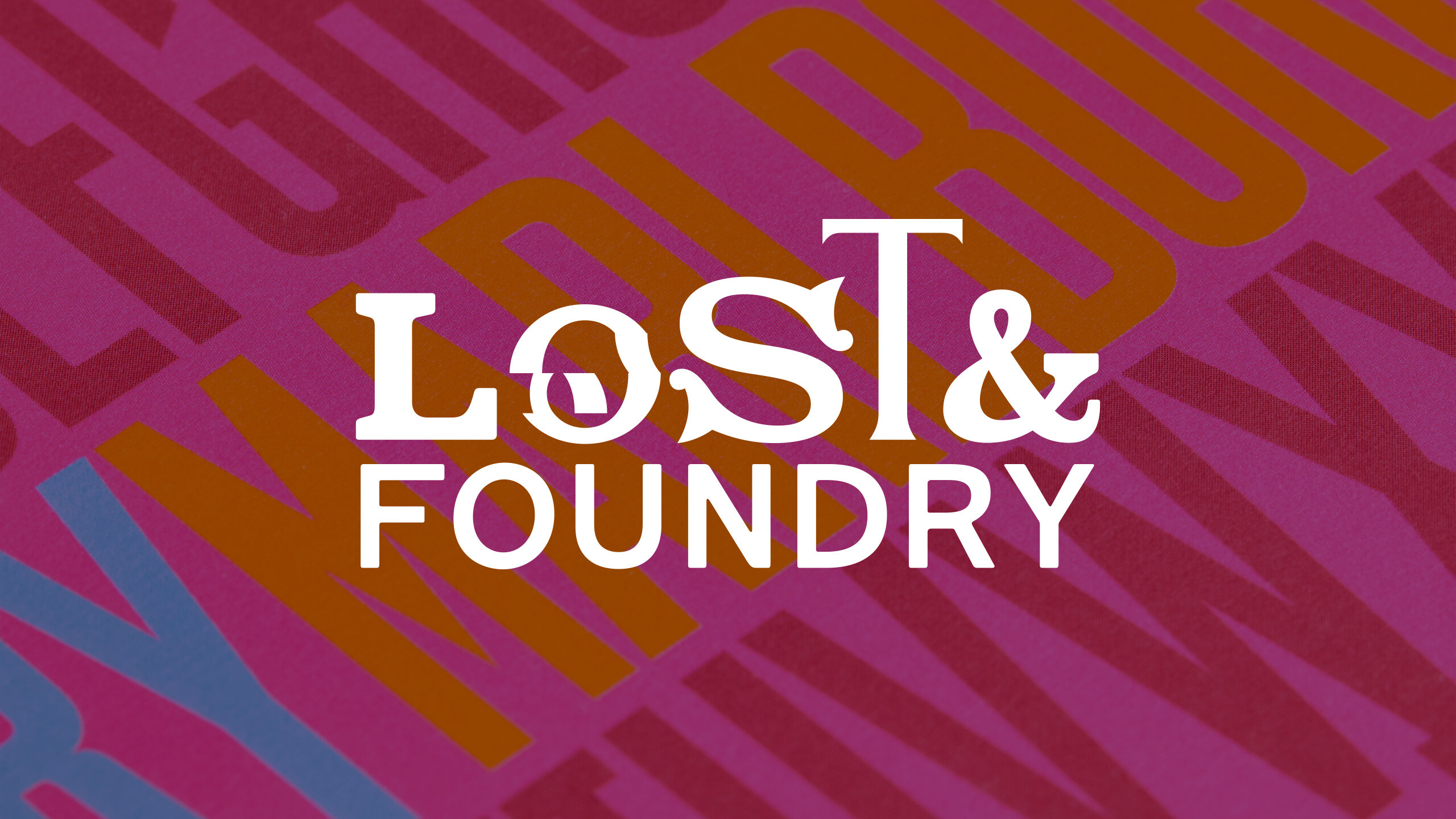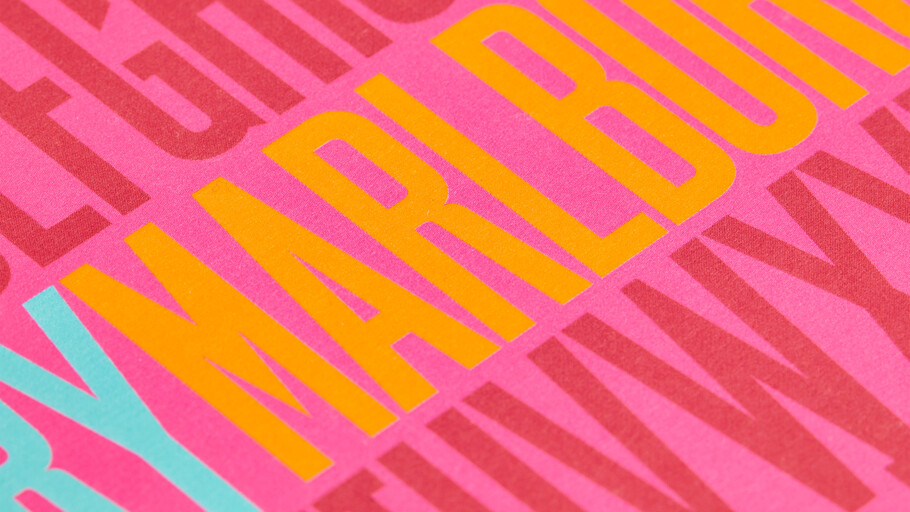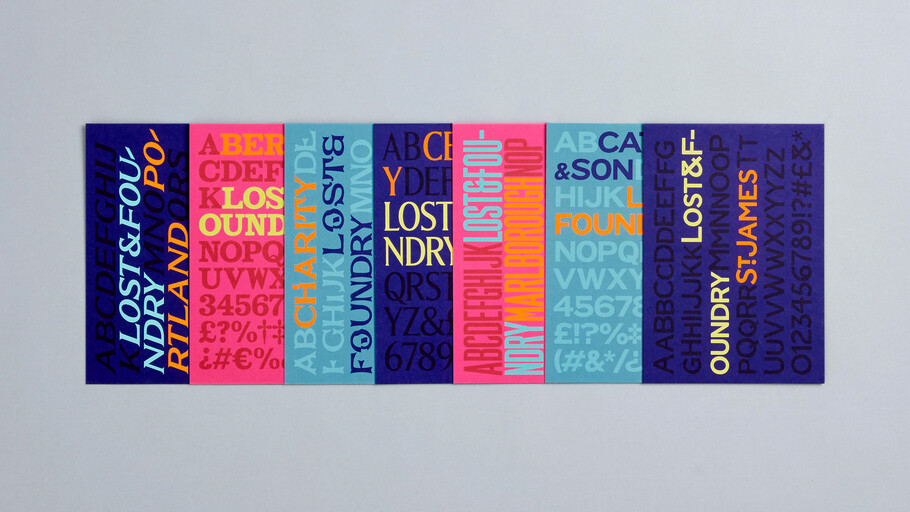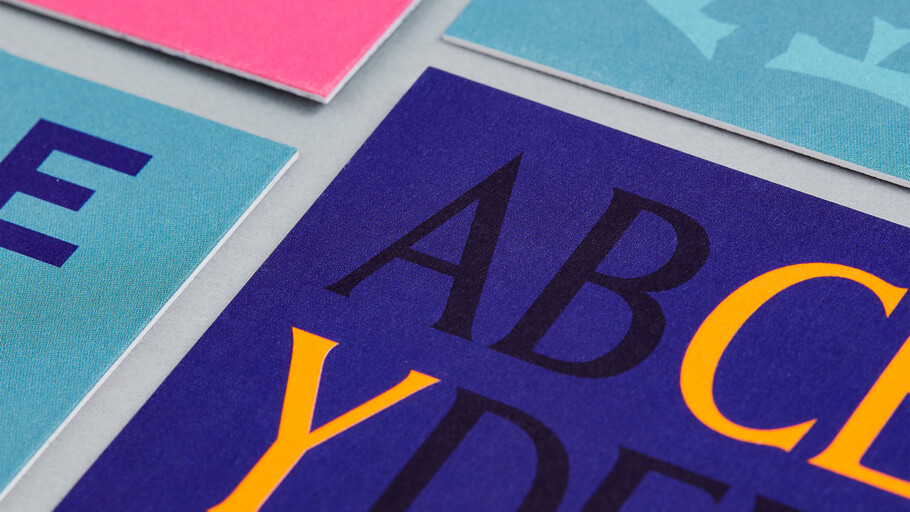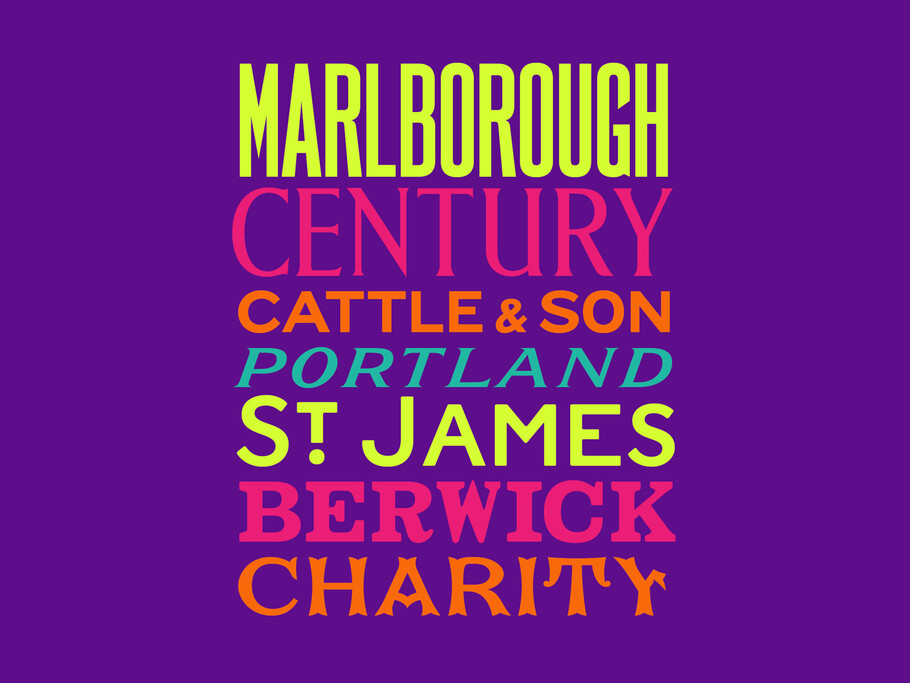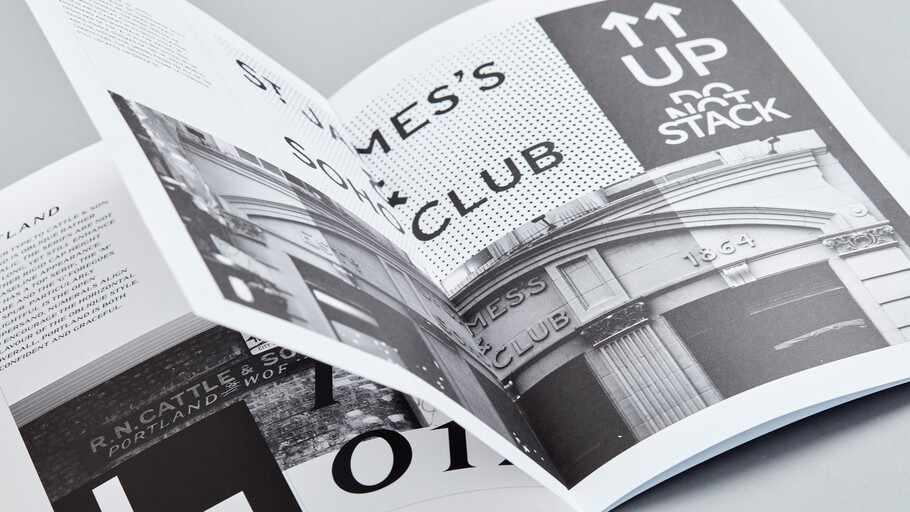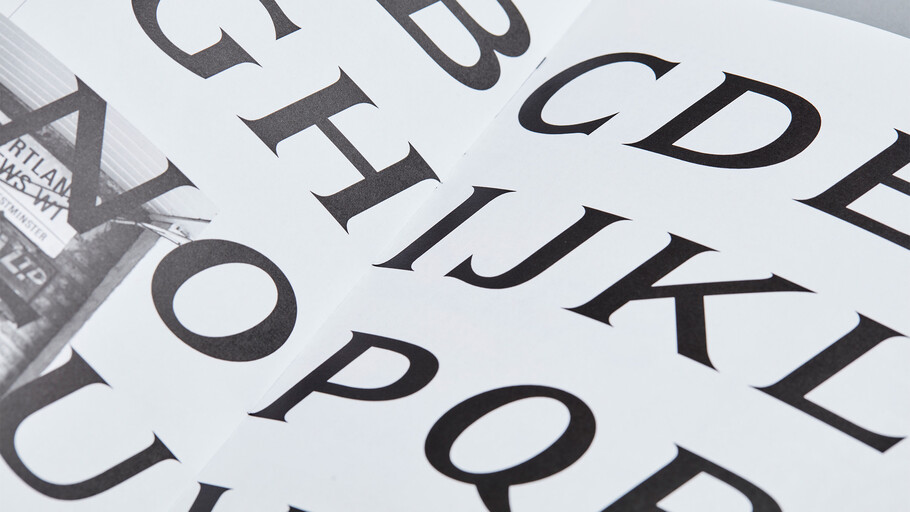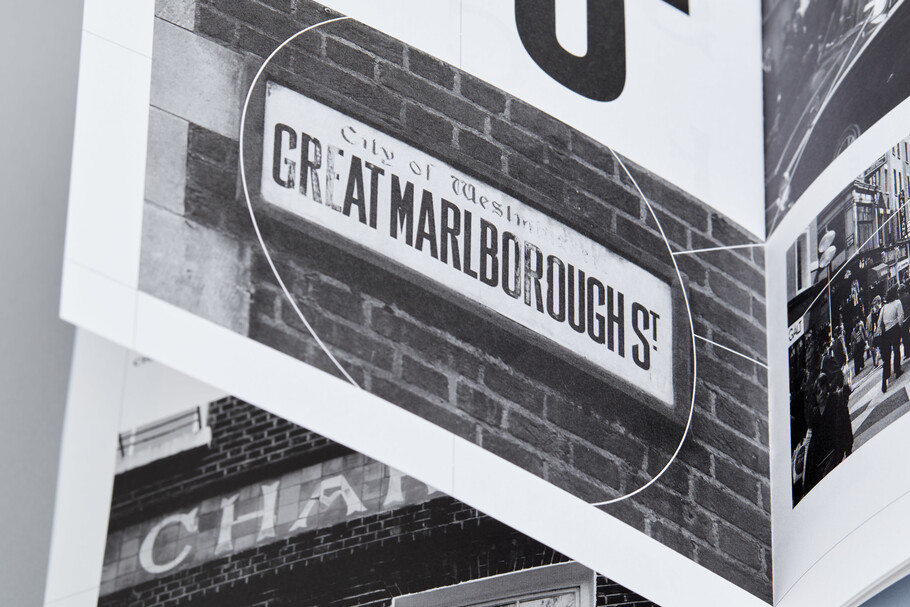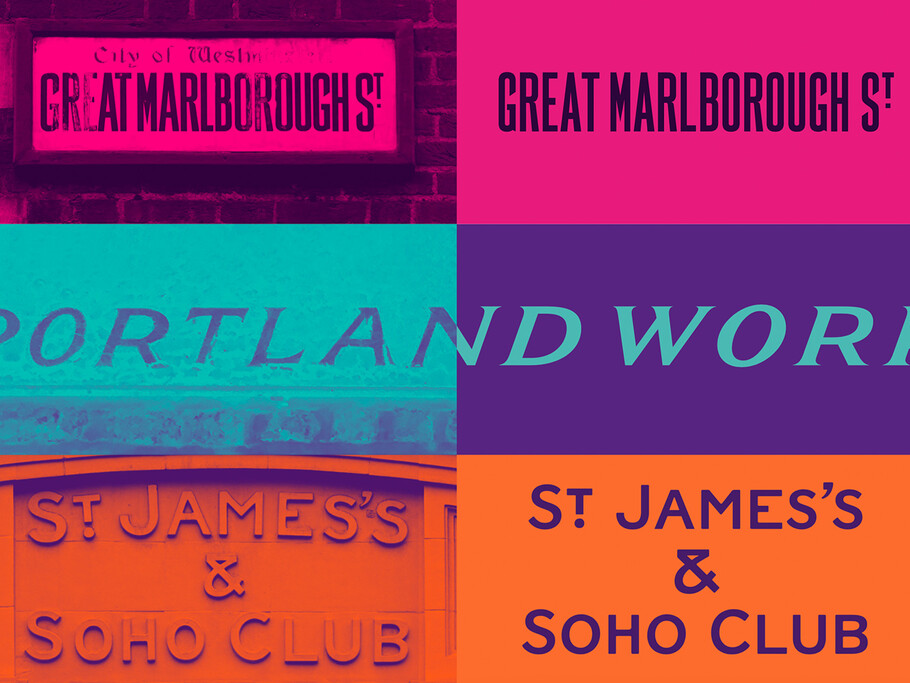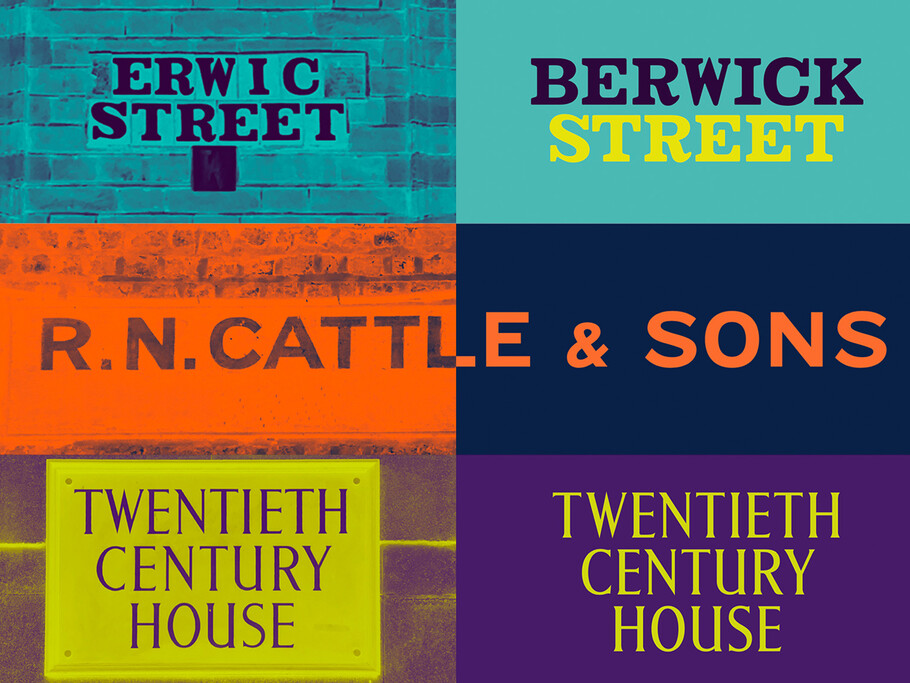
Lost and Foundry.
Fonts for good es un proyecto de Fontsmith (que ahora forma parte de Monotype Studio) y M&C Saatchi creado para reconvertir las señales y letreros antiguos del Soho en una colección de fuentes con el objetivo de recaudar fondos para las personas sin hogar de Londres.
La campaña, desarrollada por Fontsmith (ahora parte de Monotype Studio), M&C Saatchi London y Line Form Color, recupera los tipos de letras presentes en señales y letreros antiguos del Soho para venderlos en línea como una colección de fuentes de visualización. El objetivo es donar los fondos a la importante labor que realiza la entidad The House of St Barnabas con las personas sin hogar en Londres.
The House of St Barnabas es una iniciativa social que pretende romper el ciclo de sinhogarismo a través de su Academia de Empleo, un programa que colabora con personas que se han visto afectadas por la falta de vivienda y las apoya para que consigan un trabajo duradero. Para ello, la iniciativa funciona como un club cuyos beneficios se destinan íntegramente a la Academia de Empleo.
En esta campaña, Fontsmith ha trabajado con M&C Saatchi London en el desarrollo de siete fuentes inspiradas en las señales y los letreros antiguos que pueden verse por el Soho. Cada una de ellas se bautizó dependiendo del contenido específico o la ubicación en la que se encontró; por ejemplo, Berwick, Cattle & Son y Marlborough.
Antecedentes.
Lost and Foundry fue un proyecto benéfico desarrollado por Fontsmith, M&C Saatchi London y Line Form Color para ayudar a recaudar fondos para The House of St Barnabas y su labor esencial con las personas sin hogar en Londres. En la campaña se recuperaron los tipos de letras de carteles antiguos del Soho para crear una colección de fuentes de visualización y ponerlas a la venta en Internet, cuyos beneficios se destinarían a The House of St Barnabas.
The House of St Barnabas es una iniciativa social que pretende romper el ciclo de sinhogarismo a través de su Academia de Empleo, un programa que colabora con personas que se han visto afectadas por la falta de vivienda y las apoya para que consigan un trabajo duradero.
El desarrollo.
Trabajamos con M&C Saatchi London en el desarrollo de siete fuentes inspiradas en las señales y los letreros antiguos que pueden verse por el Soho. Cada una de ellas se bautizó dependiendo del contenido específico o la ubicación en la que se encontró; por ejemplo, Berwick, Cattle & Son y Marlborough.
Los diseñadores Stuart de Rozario y Pedro Arilla de Fontsmith dibujaron a mano las fuentes para después convertirlas en fuentes totalmente funcionales. En el proceso, tuvieron que adaptar y ampliar los caracteres que faltaban para conseguir diseños útiles y artesanales. Para digitalizar y diseñar una serie de fuentes viable, necesitaron tres meses.
El resultado.